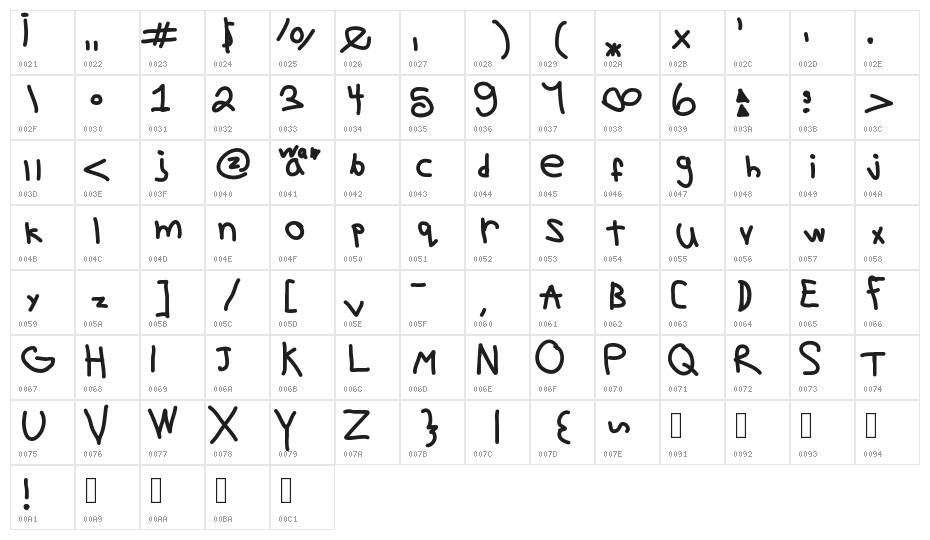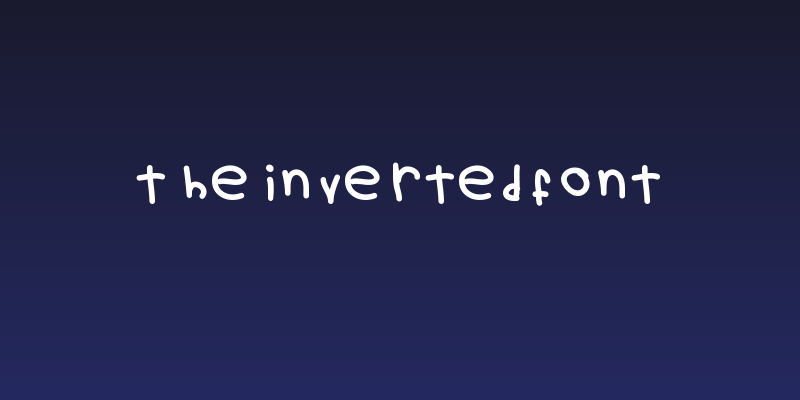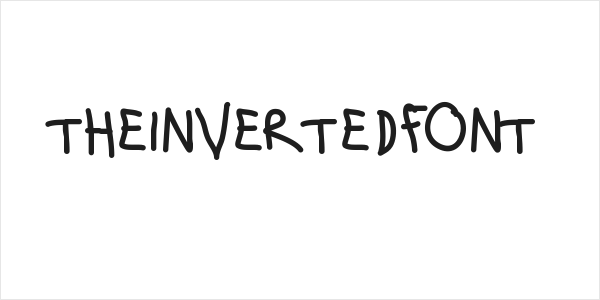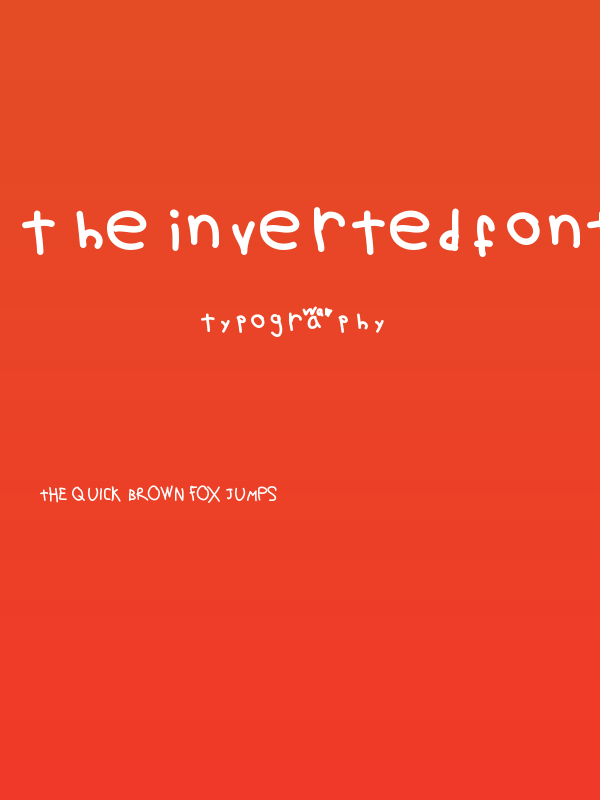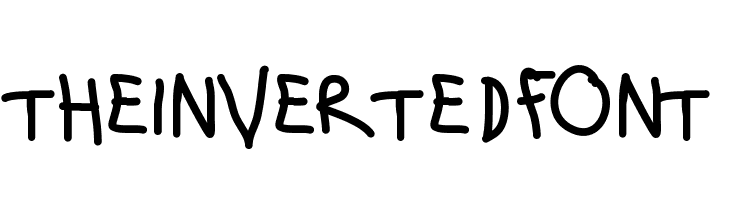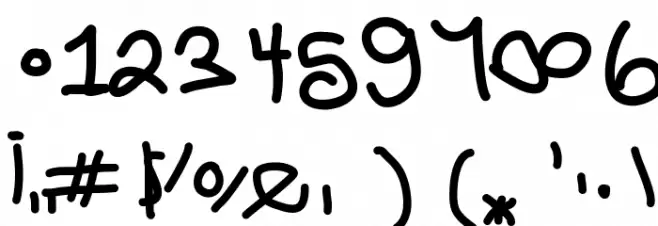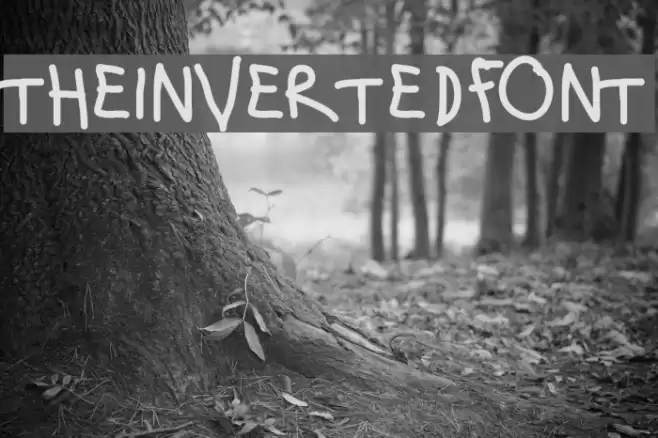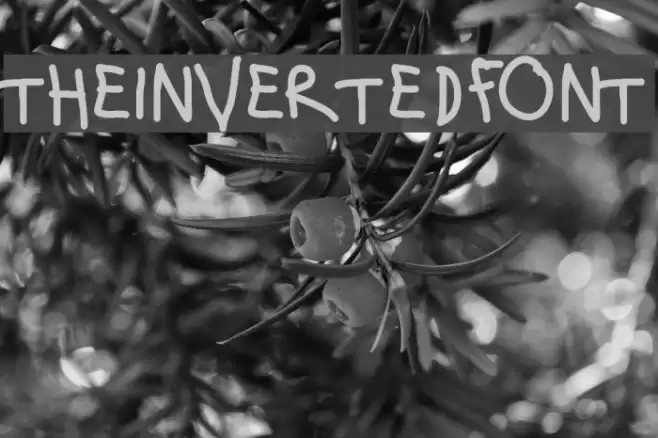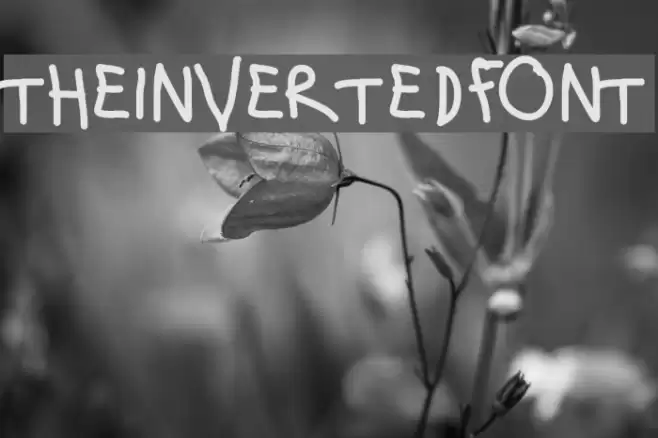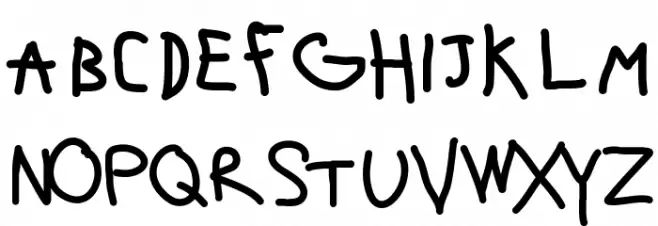
theinvertedfont Font
| Gesamtstil | Casual, Playful |
| Anwendungsfall | Headlines, Informal text, Creative projects |
| Vorgeschlagene Projekte | Ideal for greeting cards, children's books, informal invitations, and creative social media graphics. |